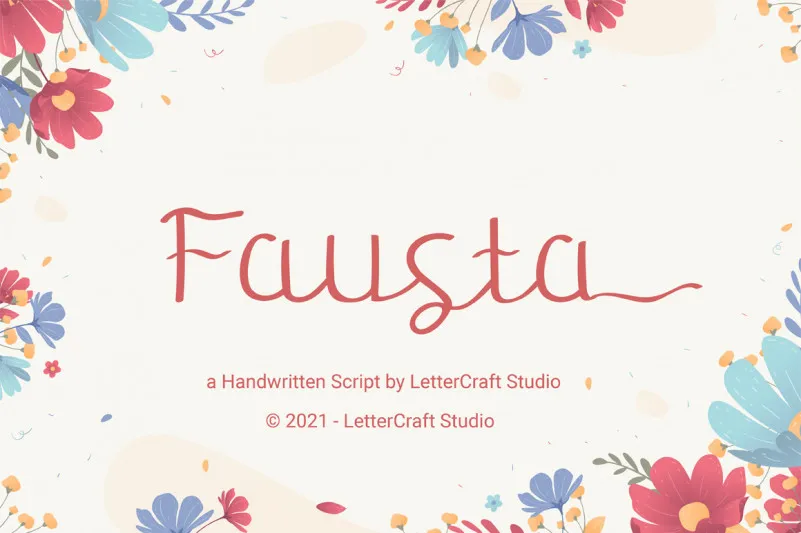
Fausta Font – Fonte Grátis
Fausta Font
A Fonte Fausta é uma bela tipografia escrita a mão, com um toque único que certamente encaixa-se perfeitamente no cenário brasileiro do design gráfico. Ideal para os criativos de todo o país, seja você designer, artista ou entusiasta da arte digital, esta fonte escreveada a mão é perfeita para projetos como aniversários festivos, cartões de apreciação e qualquer outro momento em que um toque delicado e romântico se encaixa perfeitamente. Ainda mais, a Fausta oferece uma versatilidade inigualável, permitindo-a ser usada em uma variedade impressionante de projetos desde designs para casamentos até cartões de apreciação. Para quem aprecia o trabalho delicado e a sutileza da escrita a mão, esta Fonte Fausta é definitivamente um investimento bem-vindo. Ela oferece a oportunidade de trazer uma personalização única e romântica aos seus projetos digitais. Em um país rico em beleza natural e cultura, o estilo sereno e romântico da Fausta se encaixa perfeitamente em qualquer projeto que você possa estar planejando. Seja você criando cartões de aniversário, designs de viagens para turistas brasileiros, ou até mesmo personalizando a capa de um livro local de literatura, a Fausta é uma fonte elegante e sofisticada perfeita para qualquer ocasião em que um toque suave do design gráfico pode fazer toda a diferença.